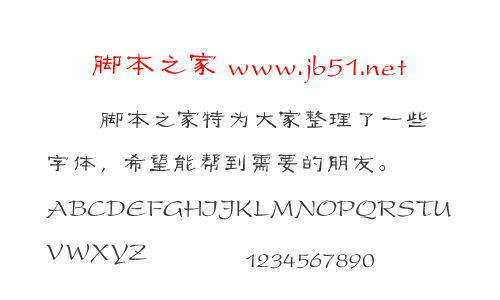
方正古隶简体字体
方正古隶简体字体是方正字体库中的一种字体,方正古隶是由书法家荆鹰先生创作。这款字体是由作者自制的竹笔书写而成,原稿字宽不到一厘米,放大后笔力仍显中正雄浑,宛如用毛笔写就。其结构巧妙严谨,大小均匀重心平稳。其风格古朴典雅,极富装饰意趣,适用于文化类的宣传设计,以及商业类品牌的广告和产品包装设计。喜欢的朋友们可以前来下载使用。